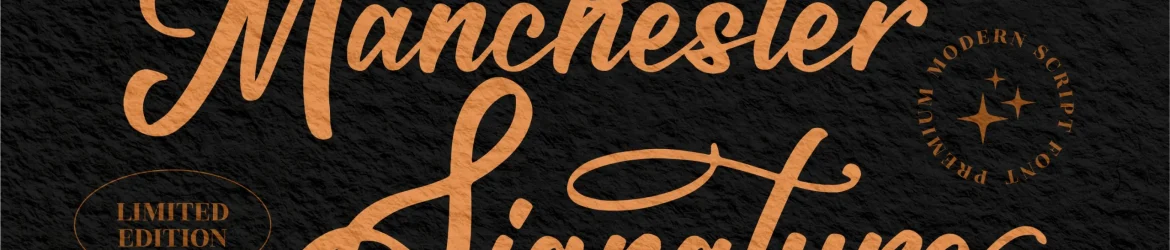
Maschester Signature Font – Download Grátis
A fonte Maschester Signature Font é uma escolha perfeita para quem busca um toque moderno e sofisticado em seu trabalho. Desenvolvida pelo estúdio Perspectype, ela se encaixa perfeitamente em uma ampla gama de projetos, desde criação de logotipos e identidades corporativas até design de embalagens de produtos, sacolas para shopping, cartões de visita e outros materiais promocionais. Suas linhas elegantes e arredondadas combinam perfeitamente com designs de homenagens, cartazes e capas de livros. Ideal para aqueles que valorizam uma grana extra em seus projetos, a Maschester Signature Font oferece um toque premium que torna sua arte ainda mais especial e sofisticada. Este é o tipo de fonte perfeita para quem busca estilo único e alta qualidade no trabalho final.